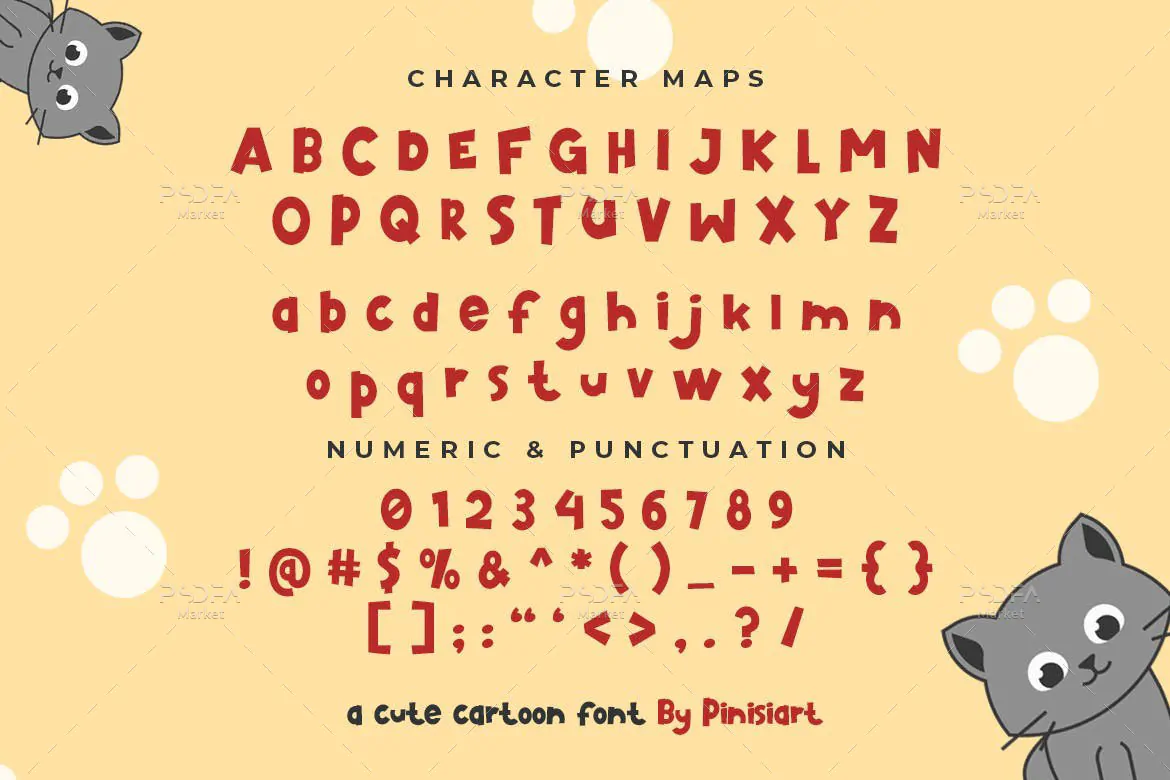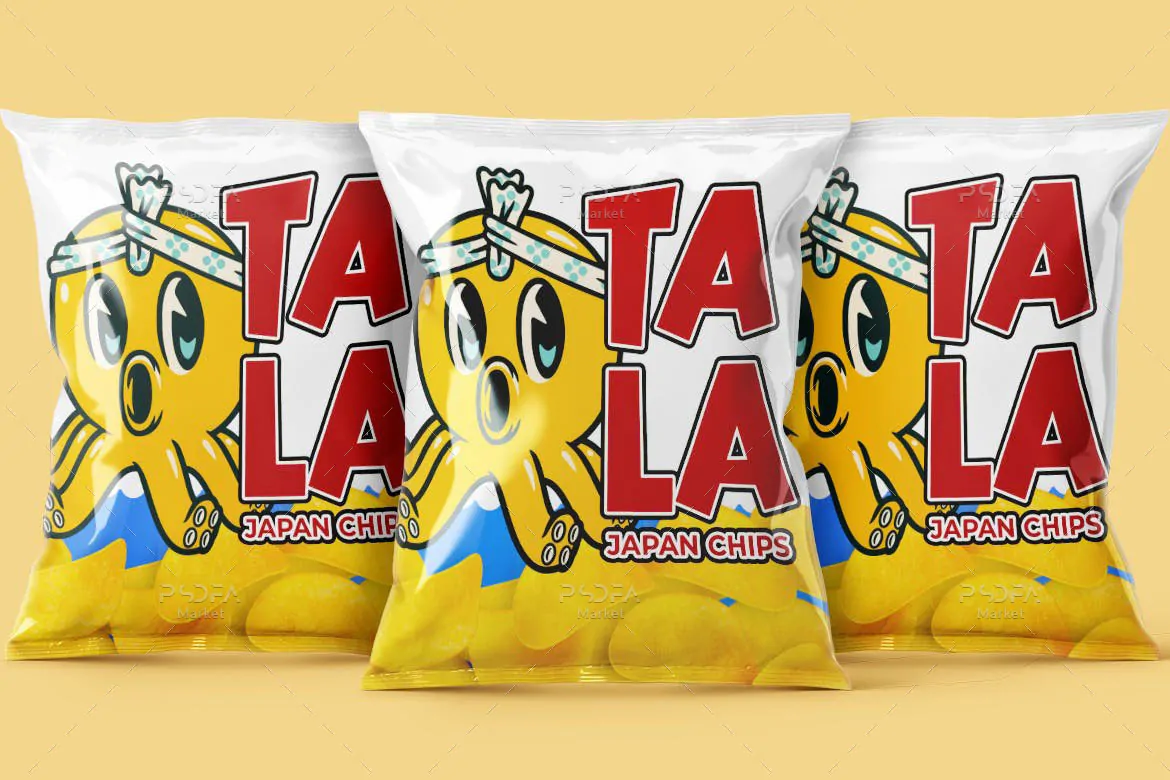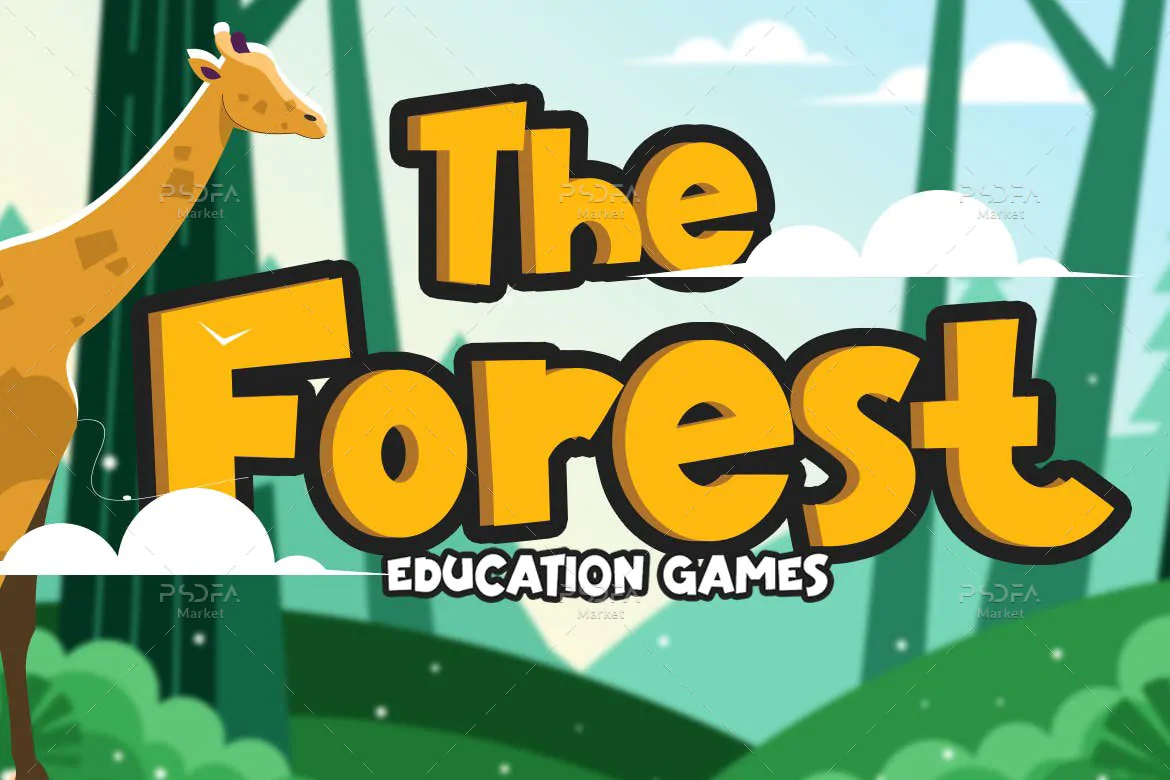
فونت کارتونی Tomcat Font
فونت کارتونی انگلیسی
فونت کارتونی Tomcat Font یک قلم انگلیسی نمایشی فوق العاده زیبا است که از آن میتوانید در طراحی و ساخت طرحهای فانتزی و کودکانه استفاده کنید. این فونت زیبا با وزن معمولی در فایل محصول قرار دارد که مناسب جهت استفاده در طراحی انواع کارت، پوستر، بروشور، بنر، تقویم، بسته بندی محصولات، ظروف یکبار مصرف، لوازم التحریر و … میباشد.